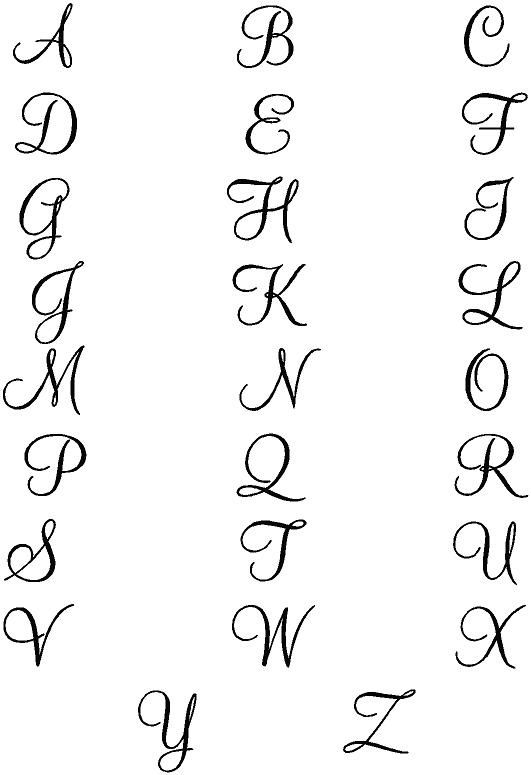
Красивые знаки и буквы для ников. Оформляем статус в вк красивым шрифтом
Вам приходилось видеть у друзей статусы Вк с необычными шрифтами? К счастью, для этого не нужно быть программистом или обладать какими-то специфическими знаниями. Интересный дизайн символов можно сделать всего за пару минут.
Делаем шрифт самостоятельно
Для этого нам понадобится стандартная программа в Windows под названием «Блокнот». Алгоритм действий или как написать статус в Вк красивым шрифтом:
После этого вы увидите, как мгновенно изменился шрифт на всей странице, включая статус.
Жирный шрифт
Жирный шрифт в статусе Вк сделать самостоятельно нельзя
Сегодня подобную задумку проще всего осуществить через те же сборники символов.
Сервисов, преображающих обычный шрифт в жирный для статуса Вк, сегодня также не наблюдается.
Смайлы и необычные значки
- Наполнить строку статуса интересными символами и знаками – намного проще. Можно использовать цветные значки, которые пользователи часто отправляют в личных сообщениях. Для этого их нужно копировать с частью текста.
Обратите внимание, что копировать смайл необходимо именно как текст, а не изображение.
В противном случае символ так и не появится в статусе. Вставив, не забудьте удалить лишнюю часть текста.
Написать статус Вк другим шрифтом не составляет особого труда, однако делает страничку намного интересней!
Воспользуйтесь значками или символами
Подборка красивых букв и символов для создания оригинальных никнеймов и ников для одноклассников и для контакта
Рукописный шрифт Beautylove
Насладитесь красотой этого классически оформленного шрифта. Объединив элементы каллиграфического и современного дизайна, этот шрифт идеален для потрясающей и в то же время простой татуировки. В этот сет включены 300 глифов и 118 альтернативных символов для дополнения вашей работы.